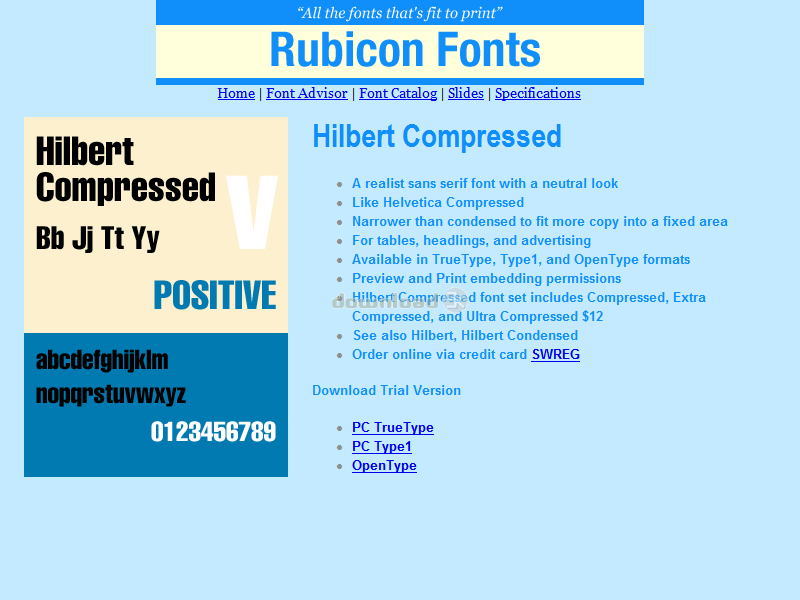
Hilbert Compressed Font Type1 2.00
"Realist sans serif font, neutral feel"
Réaliste comprimé police sans serif avec une sensation neutre. Comme Helvetica comprimé. Un design tout usage, idéal pour les tables, les titres et les publicitaires. Plus étroit que condensée. Précis et laissé entendre, ce qui correspond mesures de police, jeu de caractères standard, crénage paires. Qualité dimpression professionnelle pour jet dencre, laser, typographe à 3500 dpi. Les acheteurs reçoivent 3 variantes de police comme suit: comprimé, Extra Compressed, Ultra comprimé ..Exigences: Older versions of Windows require Adobe Type Manager.